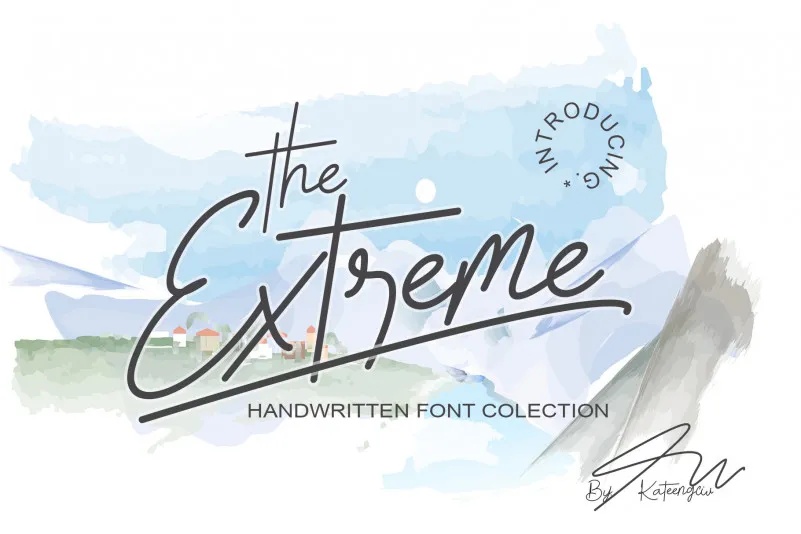
The Extreme Font – Download Grátis
A fonte The Extreme é uma escolha perfeita para quem busca um toque delicado e elegante na escrita manual. Suas letras distintas e bem redondas fazem dela algo único, capaz de transformar qualquer criação num prato cheio de visibilidade. Simples mas com um impacto visual acentuado, The Extreme é uma escolha perfeita para aqueles que desejam destacar seus trabalhos, oferecendo um toque sofisticado e delicado ao mesmo tempo. Seja você uma designer de gráficos ou criador de conteúdo online, The Extreme é a fonte ideal para adicionar elegância sem comprometer o estilo único e vibrante do seu trabalho.